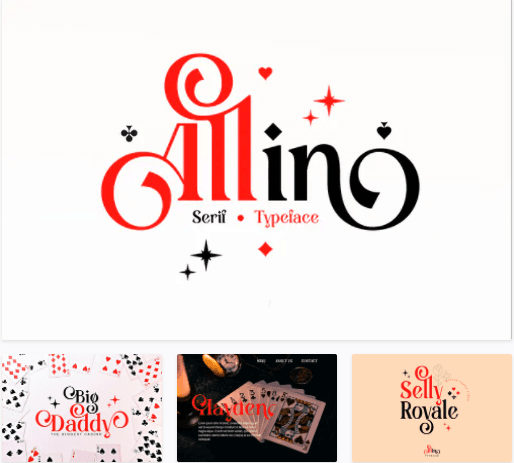
All in Font
Привет !! На этот раз я выпустил новый продукт под названием «all in», который выполнен в элегантном и современном стиле. Этот шрифт подходит для пригласительных билетов, украшений, предметов одежды, поздравительных открыток и прочего. Этот шрифт также имеет прописные, строчные, числовые, знаки пунктуации и многоязычный. и есть несколько лигатурных и стилистических альтернатив.